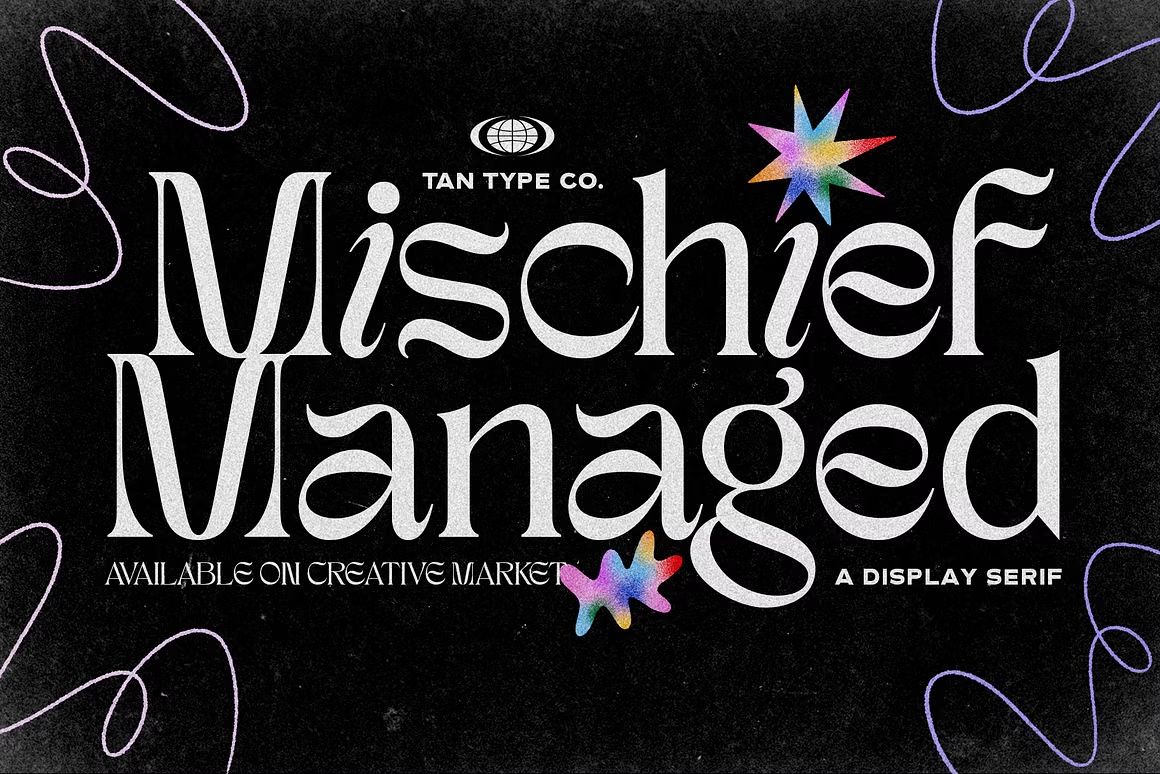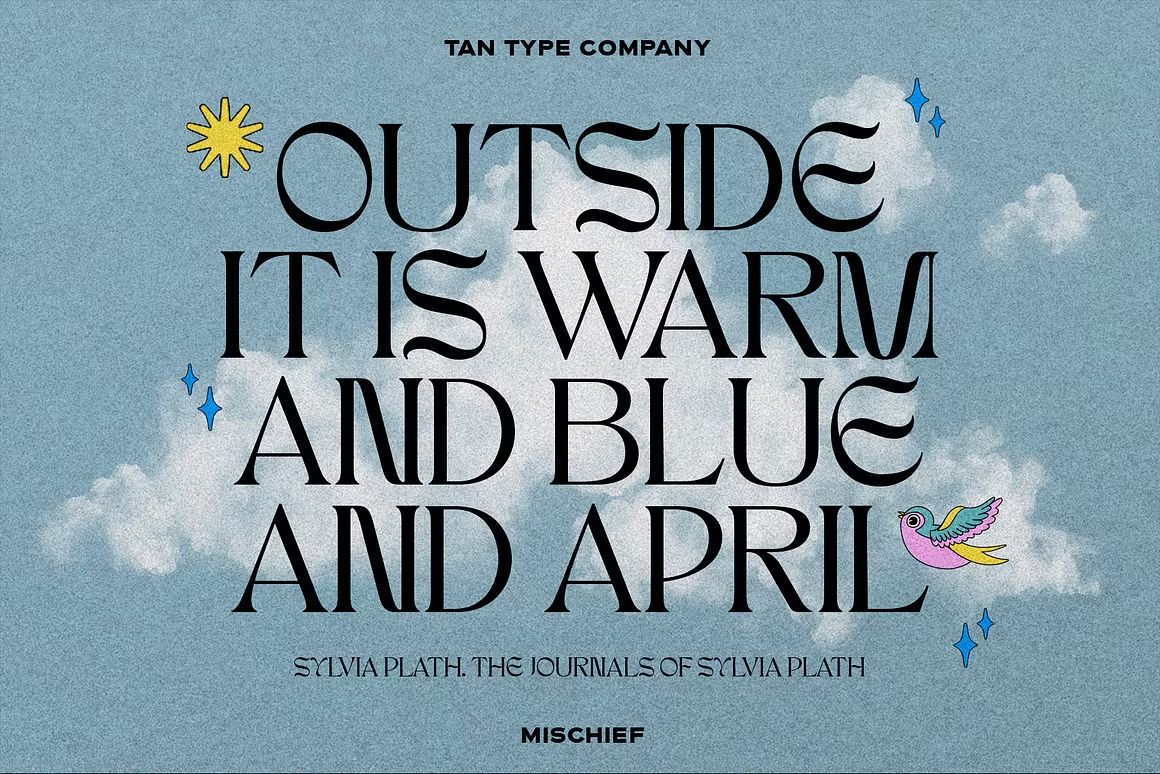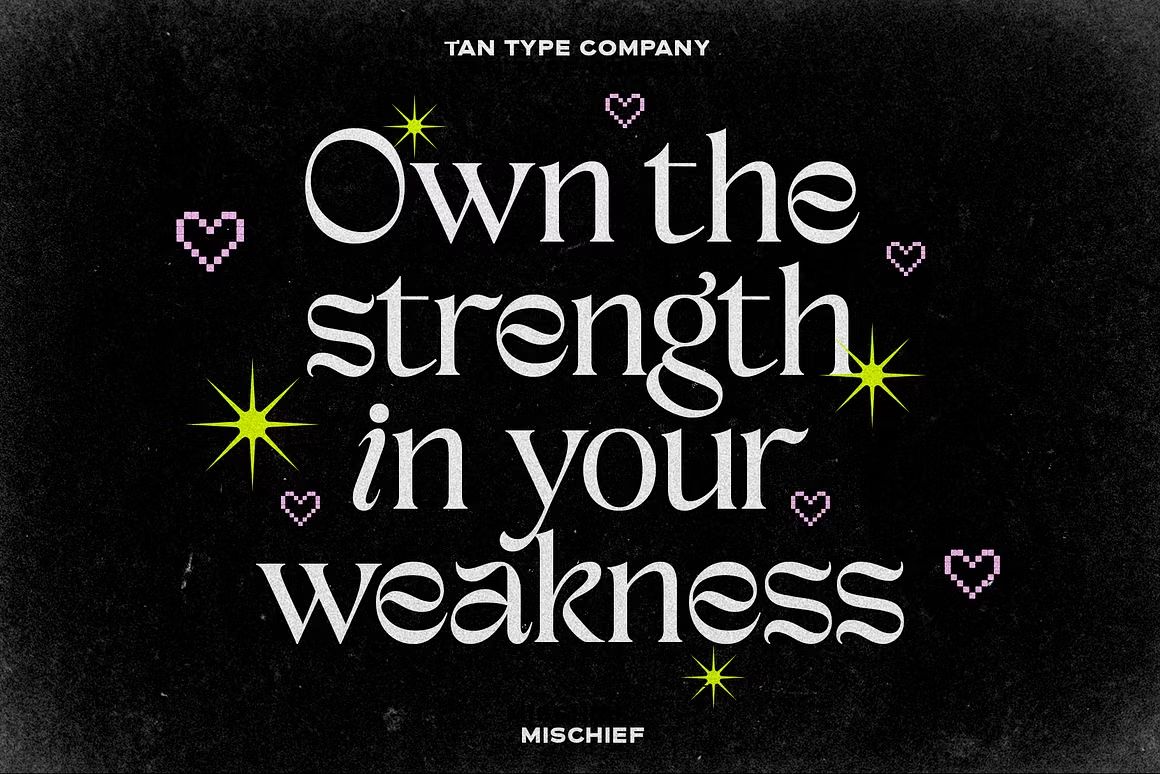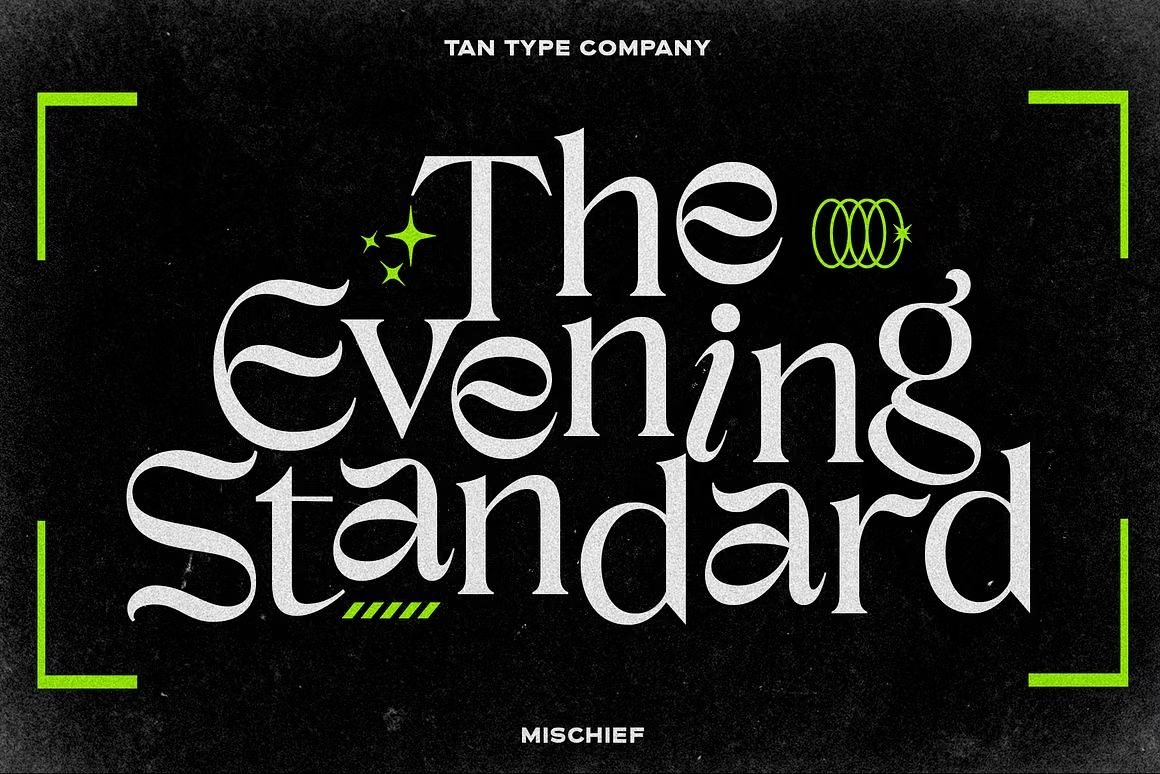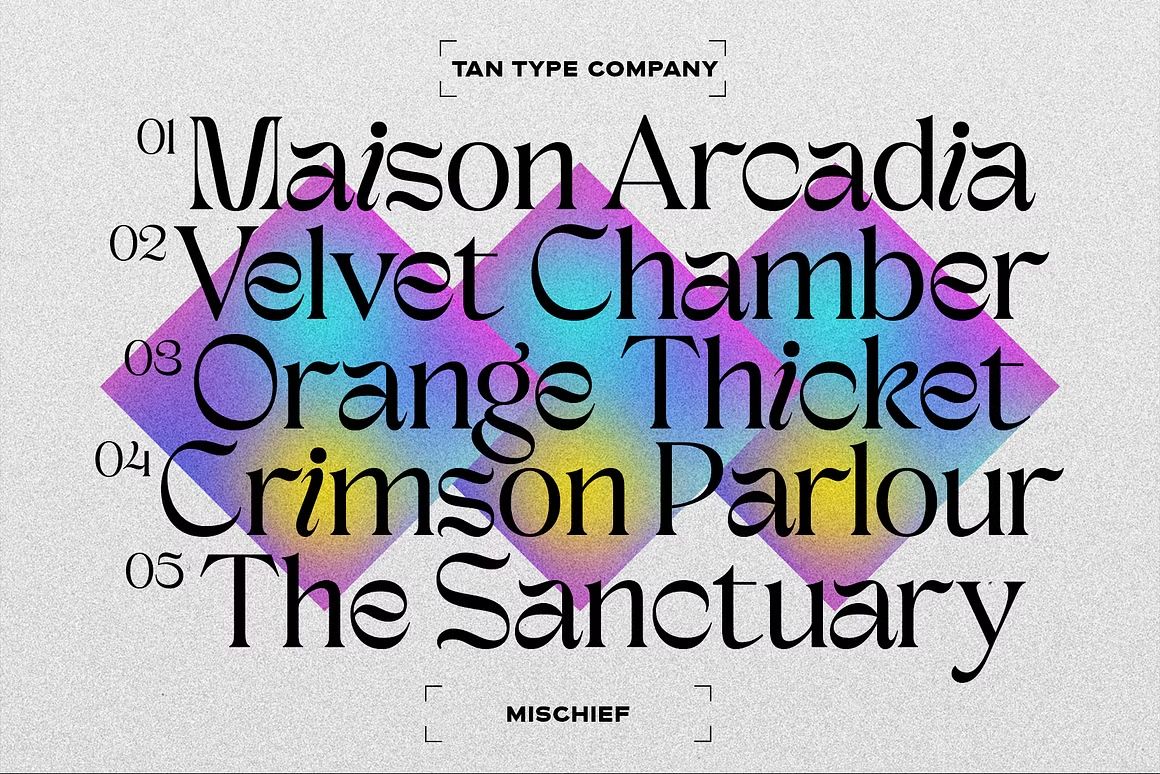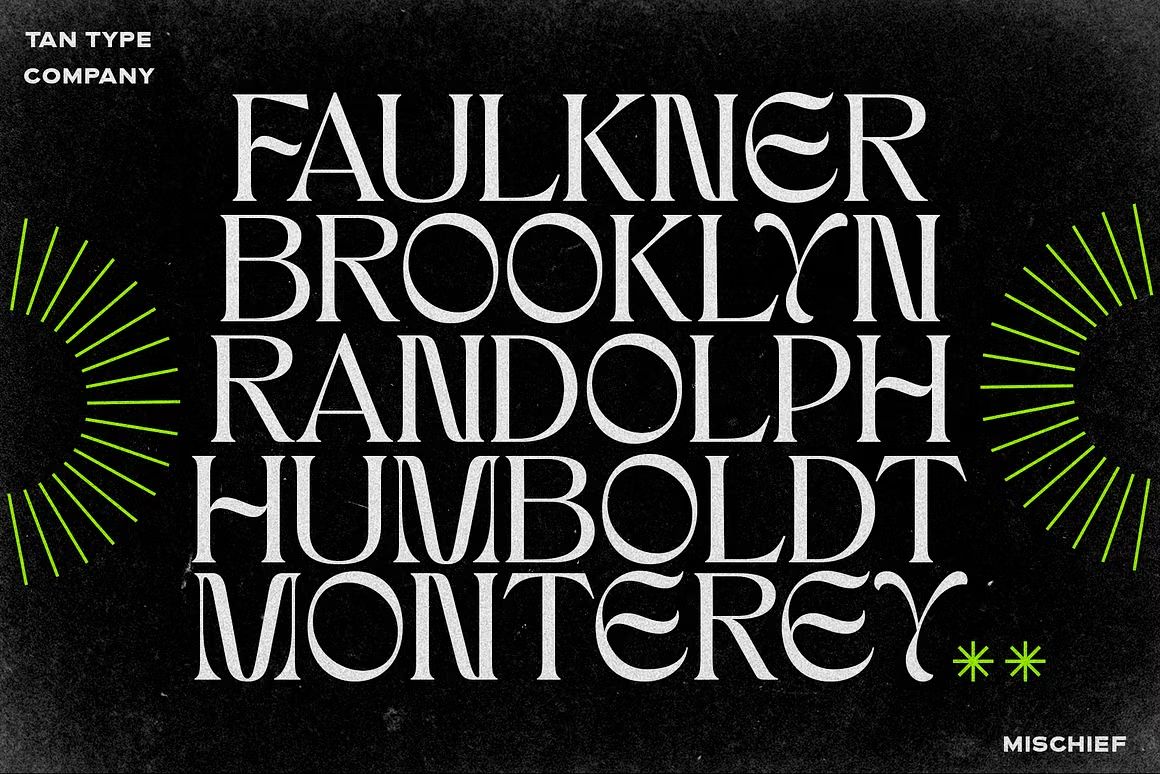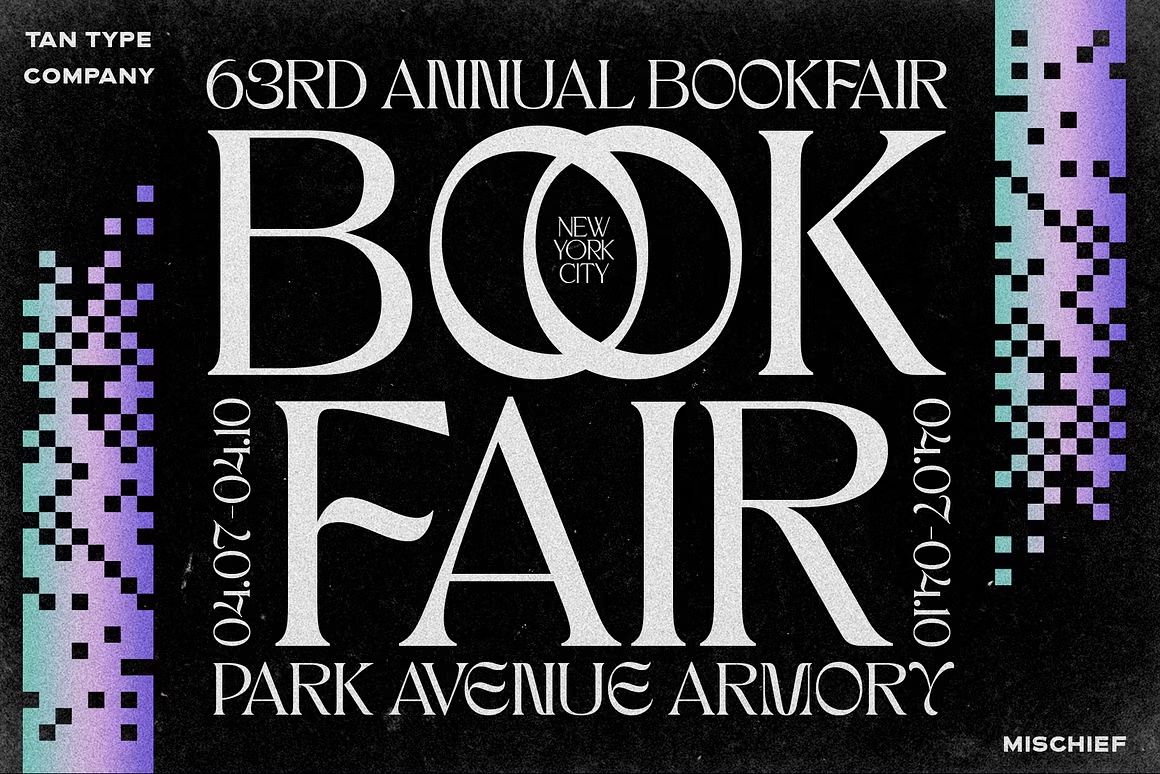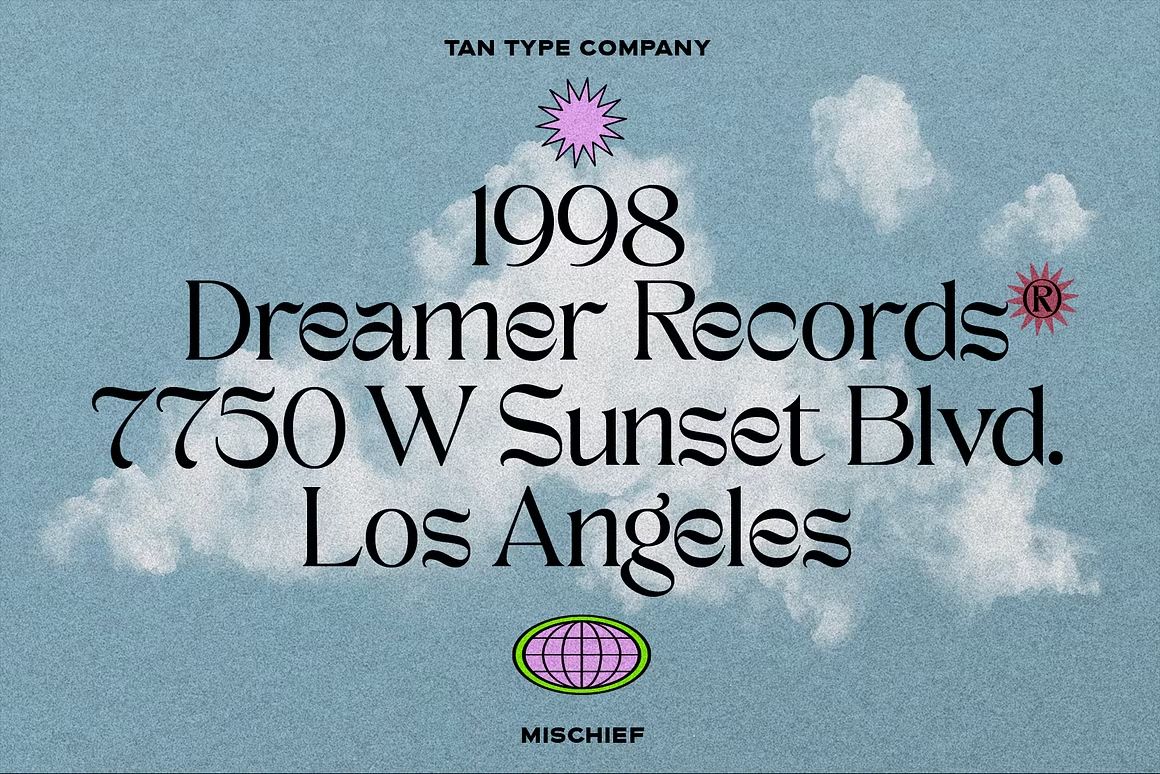
Mischief – Sans Serif Font
Mischief adalah font sans serif tebal dan playful, cocok untuk desain kreatif, ceria, dan unik. Format OTF/TTF/WOFF, siap digunakan.
Mischief adalah font sans serif dengan karakter tebal, playful, dan penuh energi. Desain hurufnya yang berani dan sedikit quirky menjadikannya pilihan sempurna untuk proyek kreatif seperti poster, kemasan produk, branding unik, desain anak-anak, dan konten media sosial yang ceria. Mischief menghadirkan tampilan yang menyenangkan namun tetap rapi dan mudah dibaca.
• Sans serif bold dengan gaya fun dan unik
• Cocok untuk poster, packaging, dan desain kreatif
• Termasuk huruf besar, kecil, angka, dan simbol